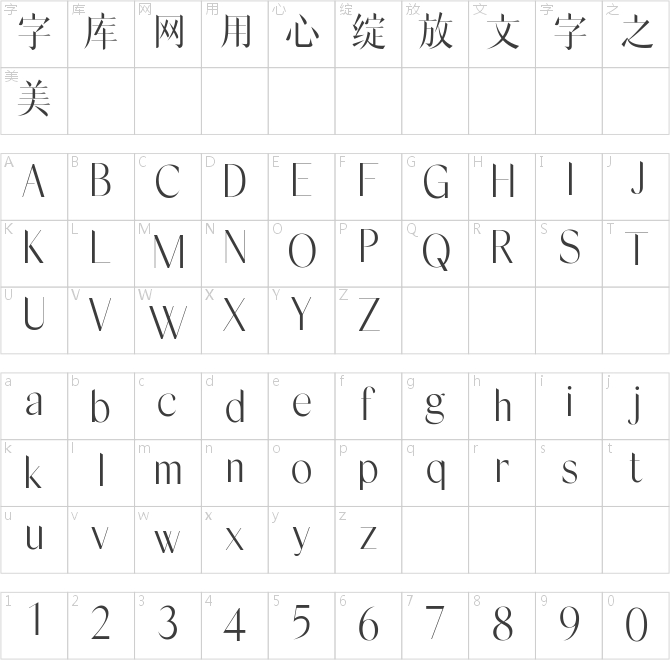
火山字型 眉月 S01 详情页
字体名称: 火山字型 眉月
火山字型 眉月 S01
火山字型 眉月 S01介绍
定位于当下视觉审美趋势,可在标题展示类应用场景中广泛使用。时尚、美妆、文化、娱乐等行业推荐使用。
眉月,采用传统宋体的小中宫处理,借鉴了港台版的旧字形风格,在体饰上尽量简化,仅保留宋体字的基本风格。外形上缩减了字面的宽度,使其呈现出修长秀丽、优雅清新之势。封口横画收笔留白,增加设计感与灵动性。各笔画的处理犀利、清劲、峻朗、风骨兼备,整体结构清晰、脱俗、内敛,有着强烈的人文气息。